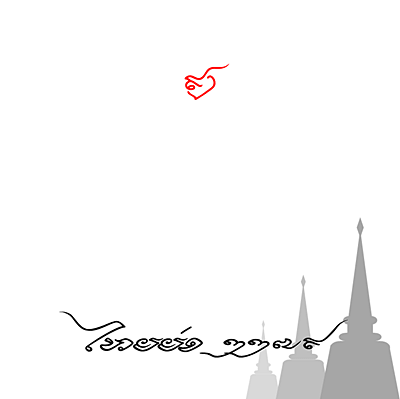
SOV_Laizen_Demo
พิมพ์ไปได้ลายเซ็น แต่ไม่อยากให้เหมือนลายเซ็นมากเกินไปจึงทำขนาดเส้นให้เท่ากันและไม่สะบัดปลายเหมือนรุ่นแรก แถมมีลายน้ำไว้ให้สังเกตว่าเป็นฟอนต์   (ถ้าไม่อยากได้ลายน้ำรบกวนลบเอาเองนะจ๊ะ)  ..ทำเป็นงานทดลองศักยภาพของการออกแบบฟอนต์ ไม่ได้เพื่อใช้งานจริง.. อย่าว่ากันนะ
SOV_maze
พิมพ์คำไหนก็กลายเป็นเกมส์เขาวงกตได้จ้า .. เล่นขำๆ สนุกๆ
SOV_Rataphan2498 (รัตพันธุ์ พ.ศ.๒๔๙๘)
ฟอนต์ตามคำขอ พระอาจารย์วัดวิเวกวนาราม ได้ส่งแบบอักษรมาให้ดู ผมเห็นว่า พ.ศ. ๒๔๙๘ คือเมื่อ 64 ปี ก่อน.. น่าสนใจ อักษรที่มีค่อนข้างเยอะ ถ้า scan รูปมาทำฟอนต์ ก็เหลือด้นอักษรอยู่ไม่กี่ตัว มีแต่ภาษาไทยนะครับ ขอขอบพระคุณเจ้าของลายมือ และพระอาจารย์มา ณ ที่นี่ด้วย
SOV_JD_Suksawad
ติดตาม Facebook อักษรตัวเขียน  ติดใจในลายมือ อ.จินดา เนื่องจำนงค์ โดยเฉพาะตัว Calligraphy ภาษาไทย ที่อาจารย์นำมาประยุกต์ใช้กับปากกาหัวตัด พู่กันแบน หรือแม้แต่กิ่งไม้เหลา จึงเก็บสะสมตัวอักษรที่อาจารย์เขียนมาเรื่อยๆ เพื่อศึกษาแนวทางในการทำฟอนต์ พบว่า ฟอนต์เดียวไม่เพียงพอ
SOV_rajadamnern
เป็นฟอนต์ตามคำขอ จากเพื่อนผู้เชี่ยวชาญภาพเก่า เรื่องเก่าๆ ในเมืองไทย… ถามว่าเคยทำฟอนต์ราชดำเนิน ตัวกลมๆ หรือยัง แล้วส่งรูปให้ดู ผมเห็นว่าเก๋ไก๋ดี ก็เลยลองทำตามแบบในรูปเก่าๆ ที่เพื่อนส่งมาให้ดูครับ นำไปใช้ได้ตามสะดวก
SOV_Kids_VF
Variable Font ที่ทำเป็นฟอนต์แปลงร่างจากตัวอักษรไปเป็นรูปภาพ เหมือนสมัยหัดอ่าน ก.ไก่, ข.ไข่, A – Ant, B – Bird เหมาะสำหรับแสดงผลบนเว็บ เพราะมีการเปลี่ยนรูปร่างได้
LYF_Mulan
ฟอนต์เฉพาะกิจ จู่ๆก็อยากจะทำขึ้นมา ต้นแบบจากโปสเตอร์ Mulan 2020 live-action ที่แสดงโดย หลิวอี้เฟย ฟอนต์ทำรูปแบบเขียนด้วยพู่กัน โดยนำมาลายเส้นพู่กันมาดัด ตัดต่อเป็นตัวอักษรใหม่ ใช้เป็นอักษรพาดหัวตัวติดๆ กันโดนเฉพาะ ไม่เหมาะกับประโยคยาว (เหมือนเช่นเคย)
SOV_JD_RungReung
เป็นฟอนต์ที่ใช้วิธี scan จากลายมือสวยๆ ของ อ.จินดา เนื่องจำนงค์ แทนการวาด vector เหมือนเคย.. แล้วบังเอิญ set ค่า parameter ไม่ดีพอ จึงได้ฟอนต์ที่ไม่สมบูรณ์เหมือนรูปต้นฉบับ..แต่ถูกใจผม จึงเลือกที่จะทำตามแนวคิด “ความไม่สมบูรณ์แบบ คือ ความงามตามธรรมชาติ”
VS_Tham_Lanxang
ฟอนต์ชุดนี้เป็นฟอนต์อักษรธรรมล้านช้าง ที่พัฒนาต่อยอดจากฟอนต์ VS ThamBali1(thamb1.ttf) โดยปรับ 4 เรื่องใหญ่
ย้ายชุดอักษรไปไว้ที่ TaiTham unicode เพื่อให้สามารถรับการพิมพ์จากแป้น TaiTham และแสดงผลร่วมกับฟอนต์ตระกูลไตอื่นๆ ได้ทำให้รองรับการพิมพ์ด้วยแป้นพิมพ์ไทย สำหรับมือใหม่ที่เพิ่งศึกษาอักษรธรรมล้านช้าง อักษรธรรมอีสาน (เช่นผม) ที่ยังไม่คุ้นการเขียนอักษรธรรม ..แต่หากชำนาญแล้ว แนะนำให้ไปใช้แป้น TaiTham จะเป็นมาตรฐานกว่าครับปรกติอักษรธรรมอีสาน ไม่ใช้วรรณยุกต์ แต่ฟอนต์นี้ทำไว้รองรับการพิมพ์วรรณยุกต์ เอก โท ได้การพิมพ์ภาษาบาลี ให้พิมพ์แบบใช้พินทุ โดยเปลี่ยนเป็นฟอนต์ตัวหนา (bold) หรือเปลี่ยนไปใช้ฟอนต์ VS_Tham_Pali
CR_Insom_Lanna
ฟอนต์ชุดนี้เป็นฟอนต์อักษรธรรมล้านนา (ตั๋วเมือง) ที่พัฒนาต่อยอดจากฟอนต์ CR_Insom 3 version โดยปรับ 3 เรื่องใหญ่